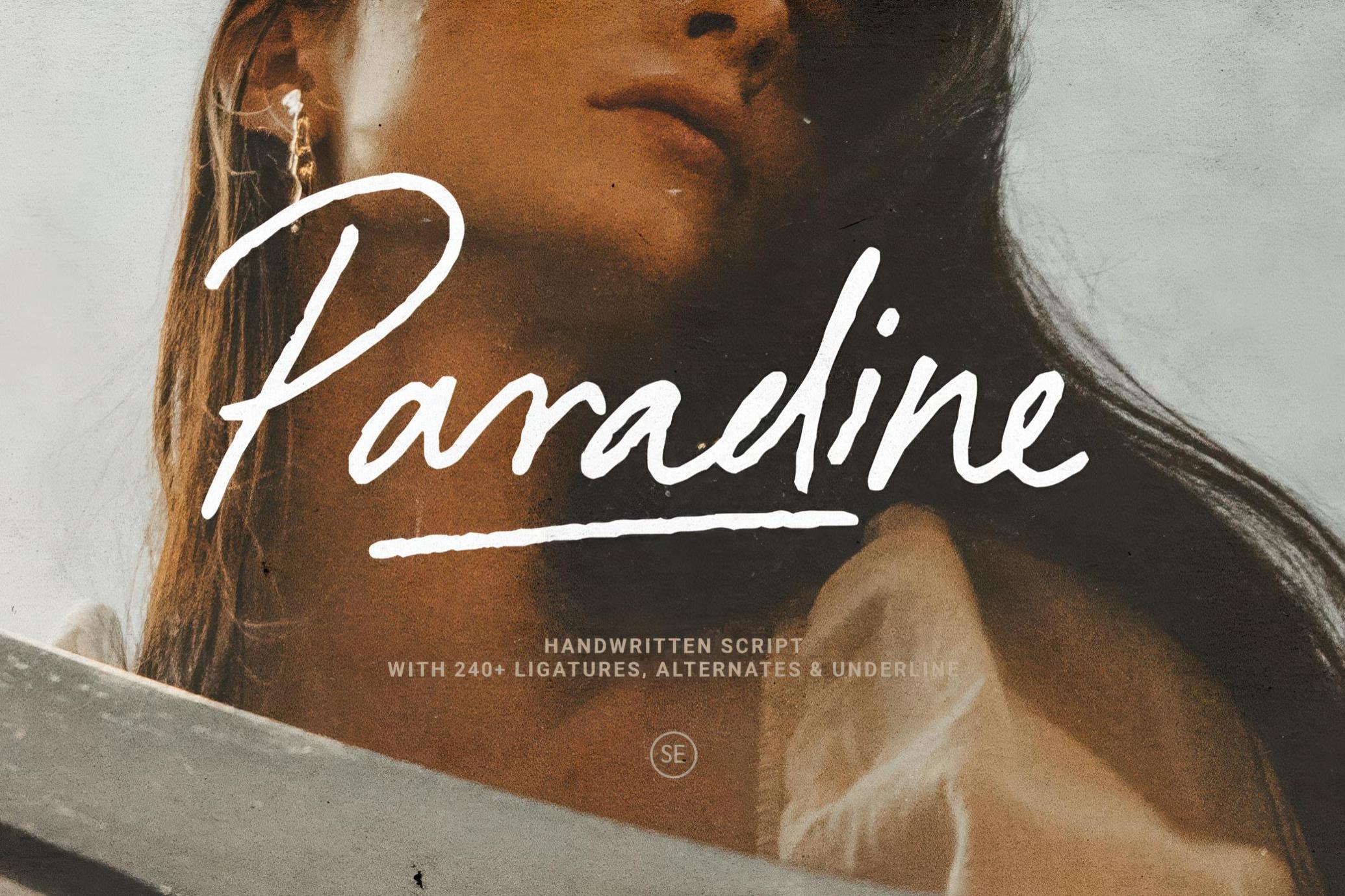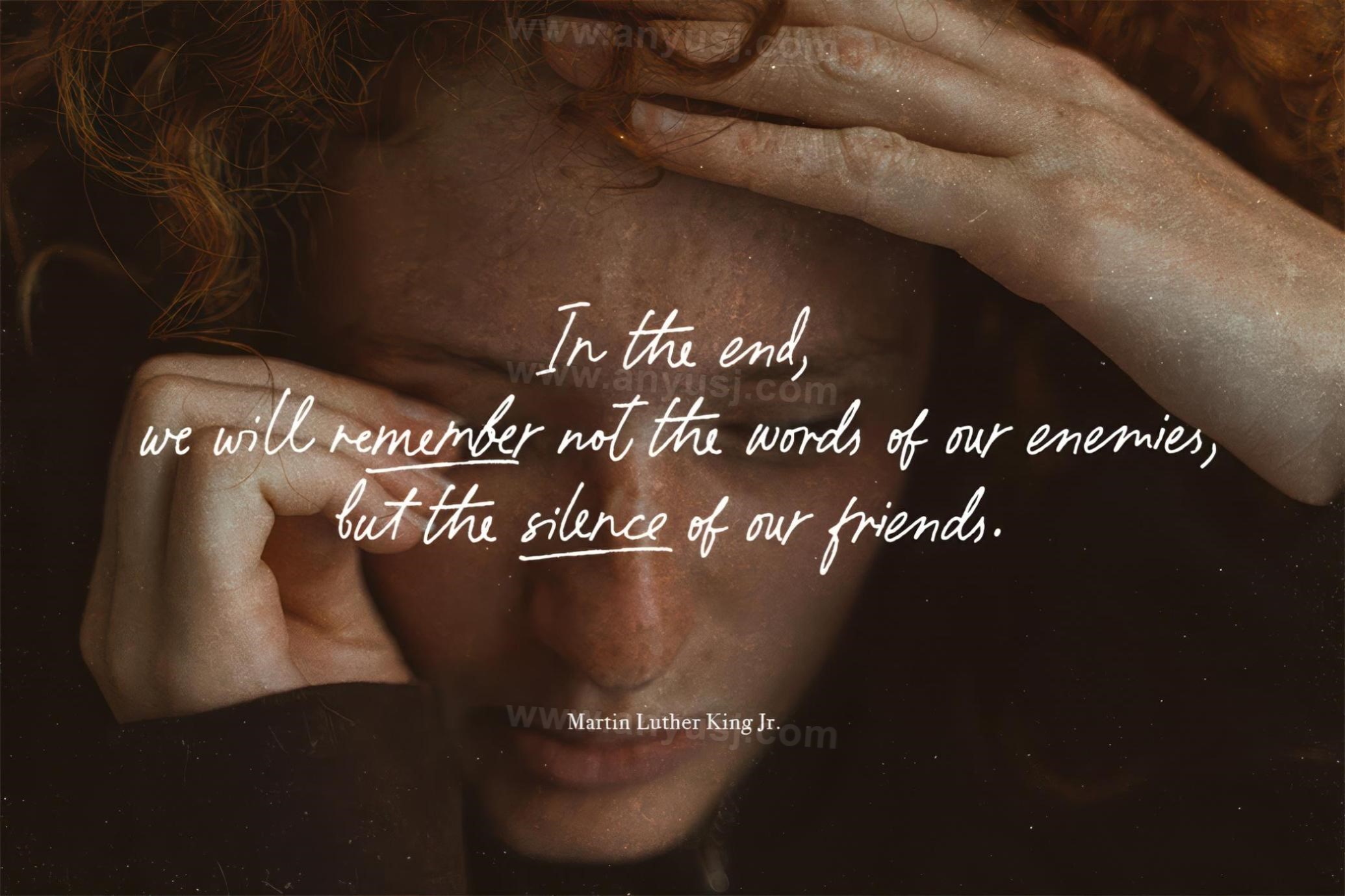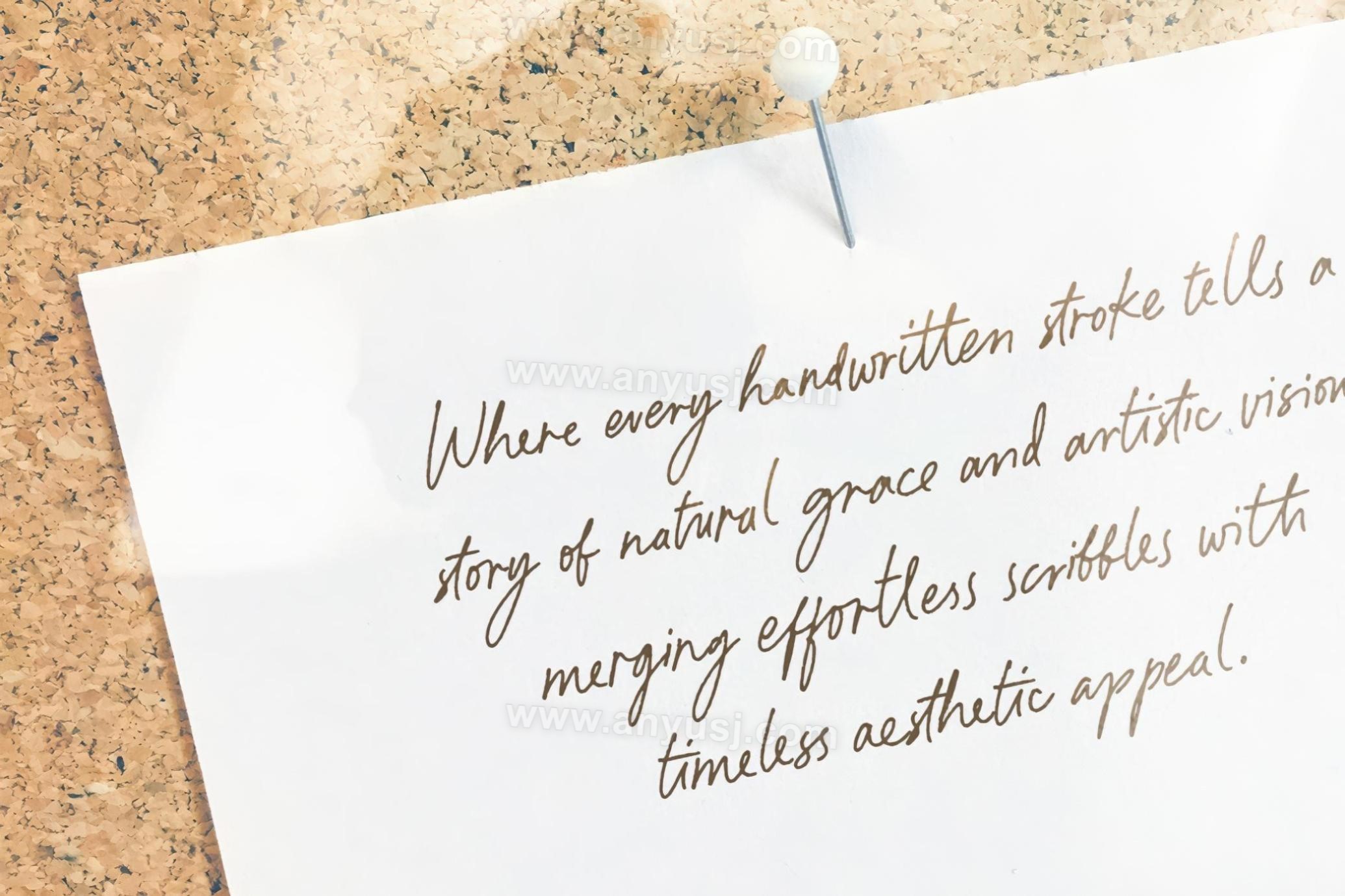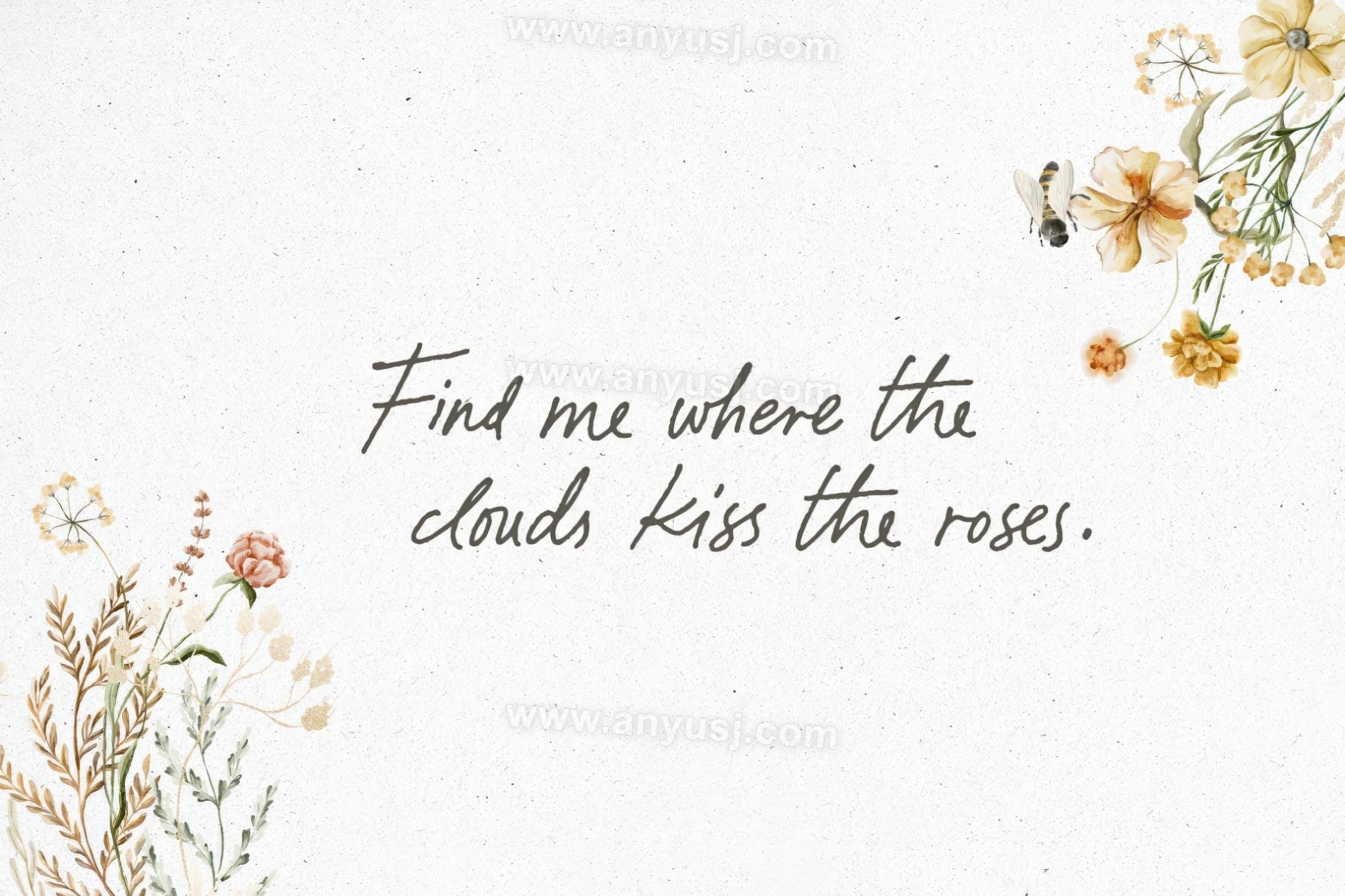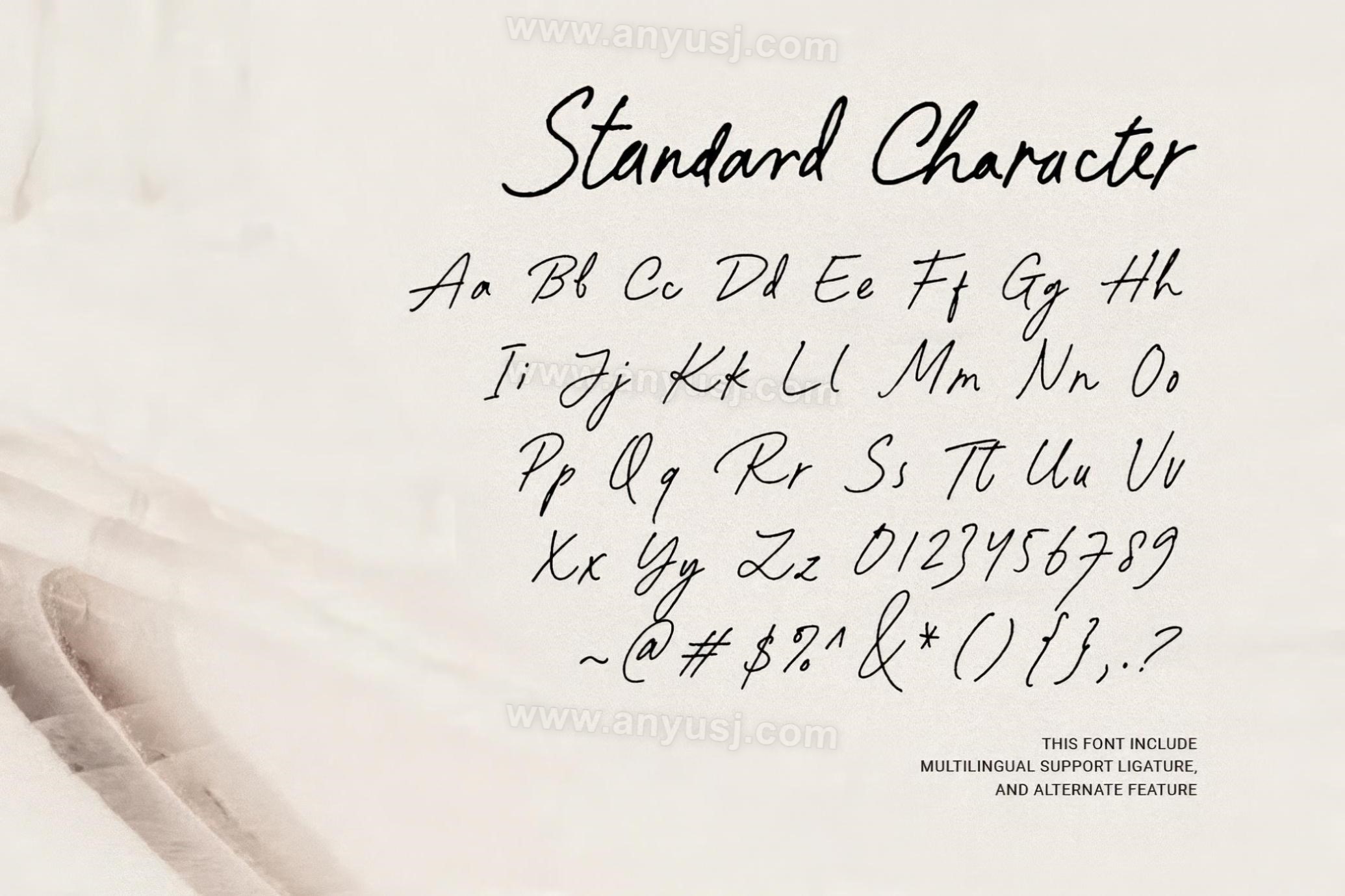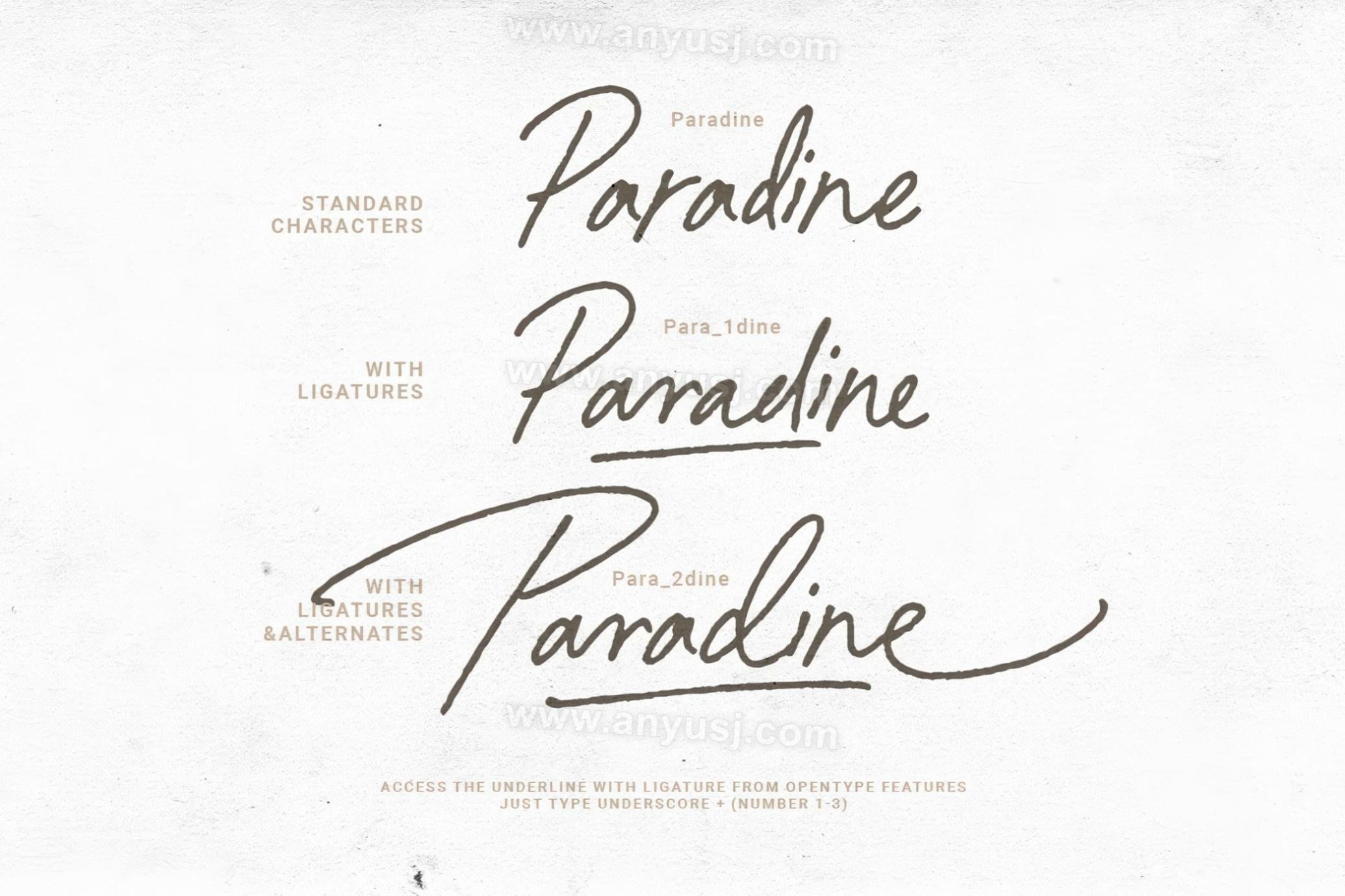
复古怀旧随意优雅放墨水logo排版标题手写英文连笔西文字体Paradine — Ligature Handwritten Font
Paradine 是一种手写字体,具有随意而优雅的画笔般的品质。它模仿自然的墨水笔触,求助于复古标牌或褪色的卡片和字母。该字体具有不同粗细的动态笔触,模仿实际的笔迹。它提供了一个完整的字符集,并辅以一堆连字和替代字符。
字体主张一种质朴和怀旧的美感,非常适合编辑设计、品牌和专辑封面。Papradine 的风格将在时尚品牌、生活杂志、专辑封面和包装中找到自己的位置,这些地方需要精致和原始个性的混合。